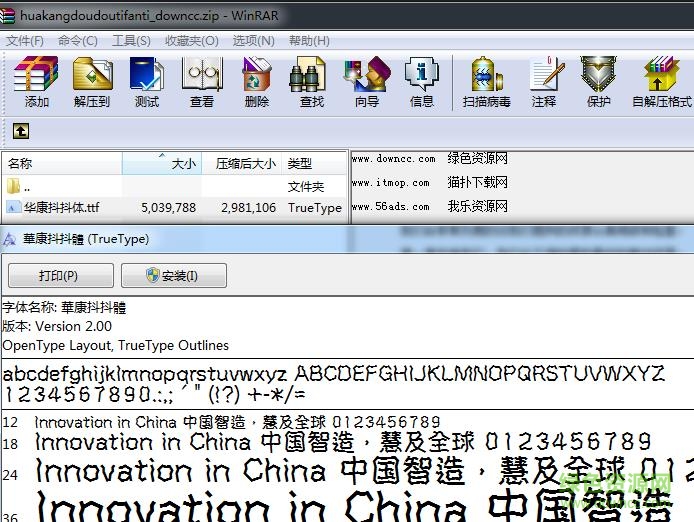
軟件介紹 軟件標簽: 華康抖抖體 華康字體 華康抖抖體字體繁體是一款能夠使用到各類設計工作當中的獨特字體樣式,讓你在電視臺字幕制作中能夠使用,當與臺灣用戶交流也可以使用繁體進行轉換,能夠達到十分不錯的顯示效果!使用說明1.通過綠色資源網(wǎng)下載華康抖抖體繁體字體2.進行字體安裝,通過右鍵單擊進行安裝3.也可將字體文件復制到C:\WINDOWS\Fonts文件夾下載! 軟件截圖 上一張下一張(1 / 1) 安裝詳細截圖 猜你喜歡 繁體字體 繁體字體 繁體字體有哪些?小編今天為大家推薦幾款好看的繁體字體,包含了繁體鋼筆字體、繁體隸書字體、繁體毛筆字體、繁體行楷字體等不同類型的繁體字體!廣告、PPT、海報、雜志等領域都可使用! 查看更多>> wow魔獸世界臺服字體包 2.40M/中文/0.0/ttf免費版下載 繁體書法字體 3.41M/中文/6.6/下載 楷書繁體字體包 9.76M/中文/8.0/下載 隸書繁體字體 5.46M/中文/4.2/.ttf下載 茶碗古刻繁體 5.37M/中文/5.0/下載 hyx4gf regular 3.41M/中文/8.0/下載 其他版本下載 標題 大小 更新日期 下載 下載地址 電腦版 華康抖抖體繁體字體 點擊報錯 軟件無法下載或下載后無法使用,請點擊報錯,謝謝! 關閉報錯反饋 請描述您所遇到的錯誤,我們將盡快予以修正,謝謝! *必填項,請輸入內容 本類最新 華康漆隸體繁w5 wow魔獸世界華康少女字體ttf 免費版 華康蕓風體w3 繁體 華康pop2體w9 p 華康粗黑體繁 dfpyuanw7字體 ttf版 用戶評論 熱門評論 最新評論 發(fā)表評論 查看所有評論(0) 昵稱: 請不要評論無意義或臟話,我們所有評論會有人工審核. 字數(shù): 0/500 (您的評論需要經(jīng)過審核才能顯示)